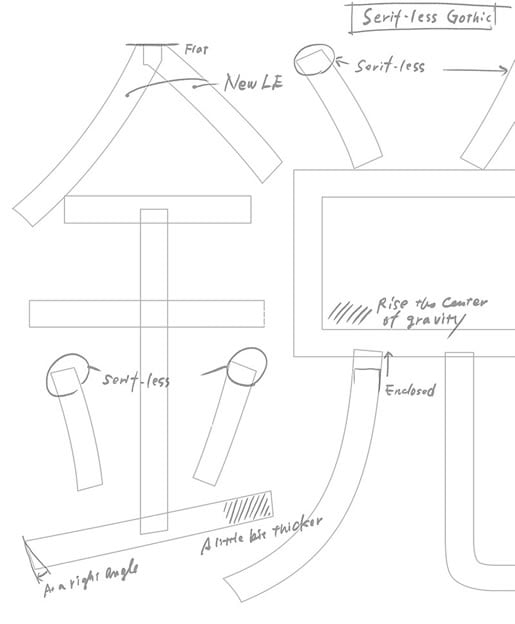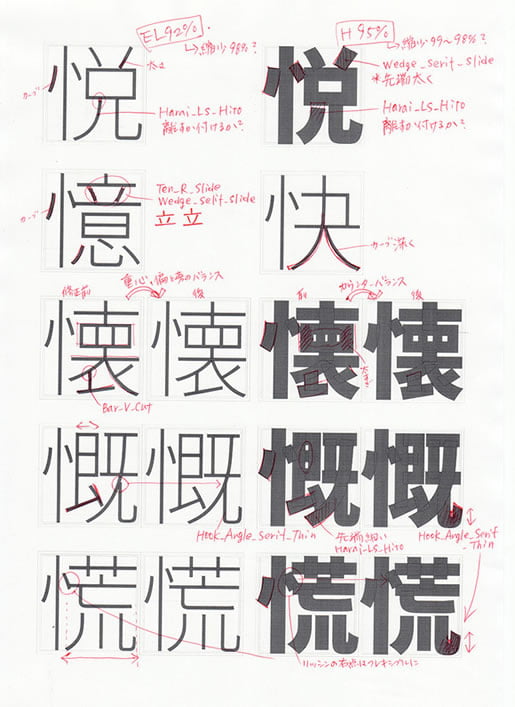
Adobe je u saradnji sa Google-om kreirao novi open source font pod nazivom Source Han Sans koji predstavlja harmoniju između istočno azijskih i Latin font dizajnova.
Fontovi za istično azijske zemlje koje zauzimaju otprilike četvrtinu svetske populacije istorijski su zasnovani na Kineskim ideogramima. Ovo je jedan od najkompleknijih Adobe font projekata čija je realizacija trajala više od 3 godine i zahtevala saradnju sa 5 različitih kompanija da bi se predstavilo 65000 karaktera koji su neophodni za kineski, japanski i korejanski jezik. Kada se ovome broju doda 7 različitih verzija fonta od Light to Heavy dobija se brojka od neverovatnih 450000 karaktera.
Font takođe pokriva sve potrebne regionalne varijacije karaktera u okviru svakog od jezika. Ovo je naročito značajno za korisnike iz Hong Konga, Tajvana i nekih istočno azijskih zemalja gde su ovakve varijacije neophodne.
Pored podrške za istočno azijske karaktere, font takođe omogućava tradicionalna latinična, grčka i ćirilčna slova iz Source Sans familije.
Krajnji rezultat je najveći open source font koji je ikada kreiran.
Benefiti ovog projekta
Source Han Sans font je veliki poklon za autore e-knjiga, programere open source aplikacija i korisničkih interfejsa. Pored činjenice da je besplatan za distribuciju, dizajniran je da bude jasno čitljiv na različitim tipovima uređaja, poput tableta, pametnih telefona, pa čak i onih najmanjih dimenzija.